02《高级感和传统感》
字体结构中,西文的衬线体比无衬线体更有高级感,而中文宋体要比黑体字更有传统感。衬线体大多由曲线组成的,虽然只有很小的曲线组成,但这些曲线搭配出的字体,却能营造出柔美而华丽的美感。
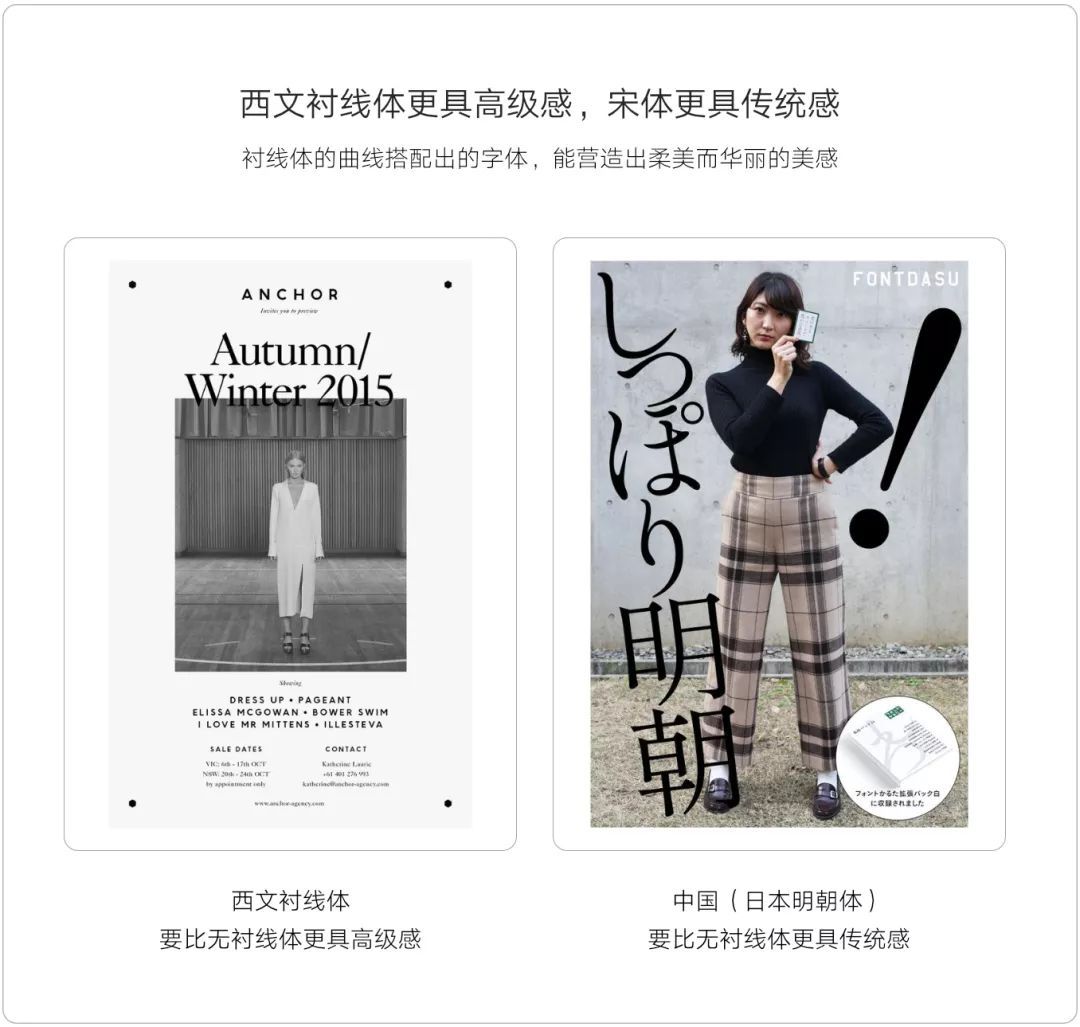
另外想要营造出“高级感”,应要在文字周围多留一些白;在颜色的处理上也不能过于艳丽,降低明度与纯度营造一种沉稳的感觉;文字与文字的距离也不能过窄,尽量让文字之间的距离留多一些白;字号也不能过大,字的颜色要选用灰阶色(黑白灰),颜色也不能过于艳丽。
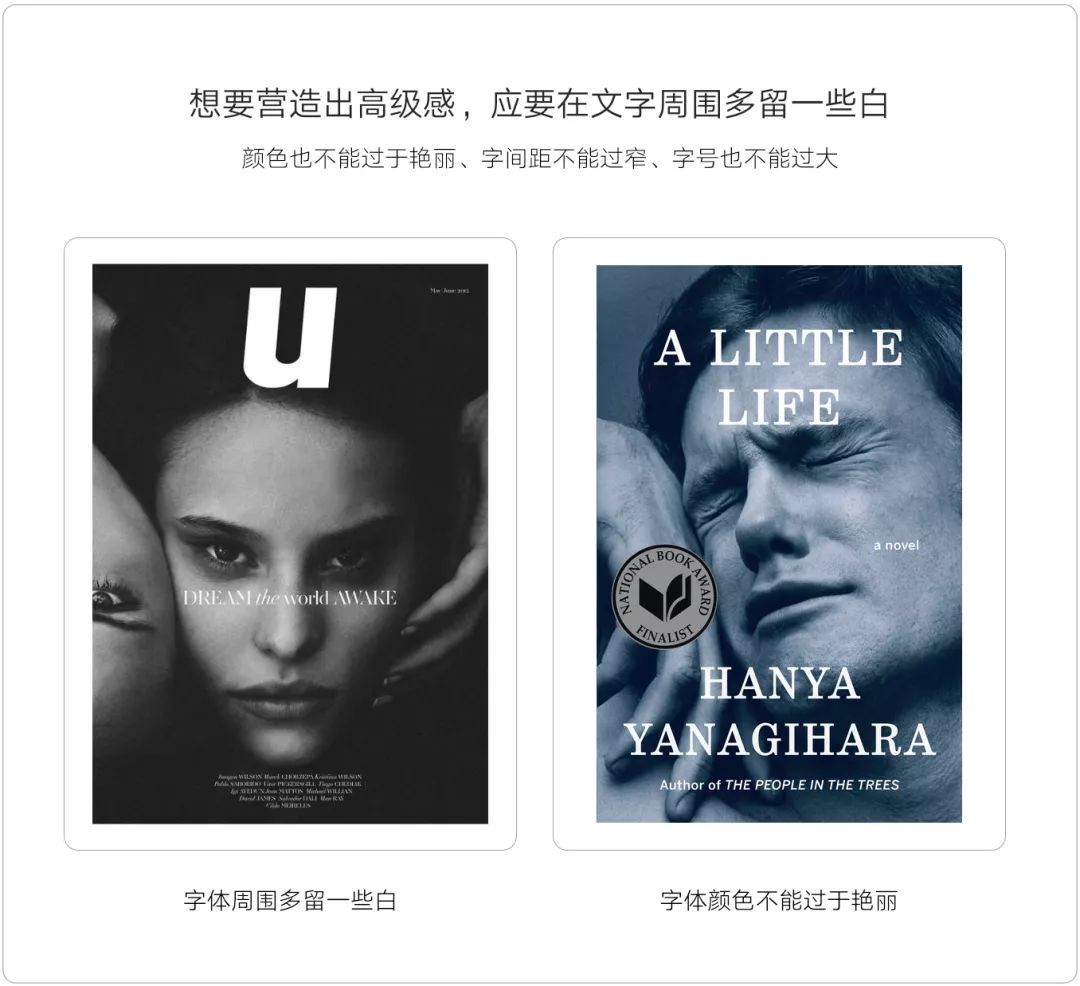
营造高级感也是有一些规则约束的。“配图没有高级感”、“字体选用不对”和“文案与图底关系不明确”都不会营造出高级感。
02《亲密感和柔和感》
生活中如小刀,锥子和针等尖锐的物体会给人一种紧张感和危险感。文字也会让人产生同样的心理。
字体线条越纤细,前端越尖锐,给人感觉就越冰冷,危险,难以靠近的感觉。相反的,不管是在自然界还是在生活中所接触到的人工制品,圆润的形状会给人安全,安心,亲密的感觉。线条粗大,前端越圆润的字体,不会让人感觉到紧张感和危险感。这种字体会给人一种易于亲近,柔和,轻松的感觉。
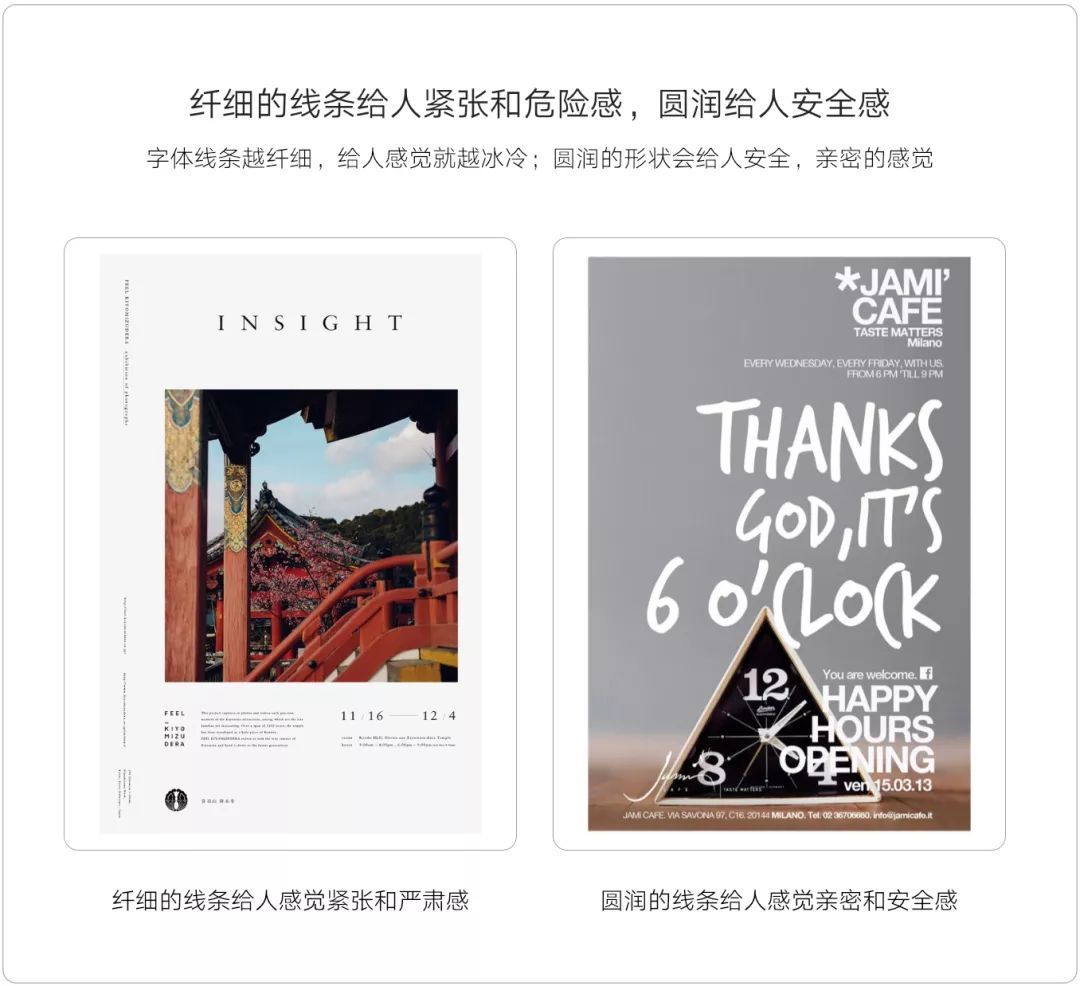
进一步说,如果想加深亲密感和柔和感的印象,可以采用类似手写字的文字设计或样式。我们知道无衬线体(黑体字)要比衬线体(古典字)更具有冷峻感和机械感。
所以用无衬线体不太好营造柔和感,做母婴类等主调较为柔和的项目时尽量用手写体和衬线体,来突出与消费者之间的亲密感和人文感。如果非要用到无衬线体(黑体字),也要尽量采用幼圆的黑体字来营造柔和感。
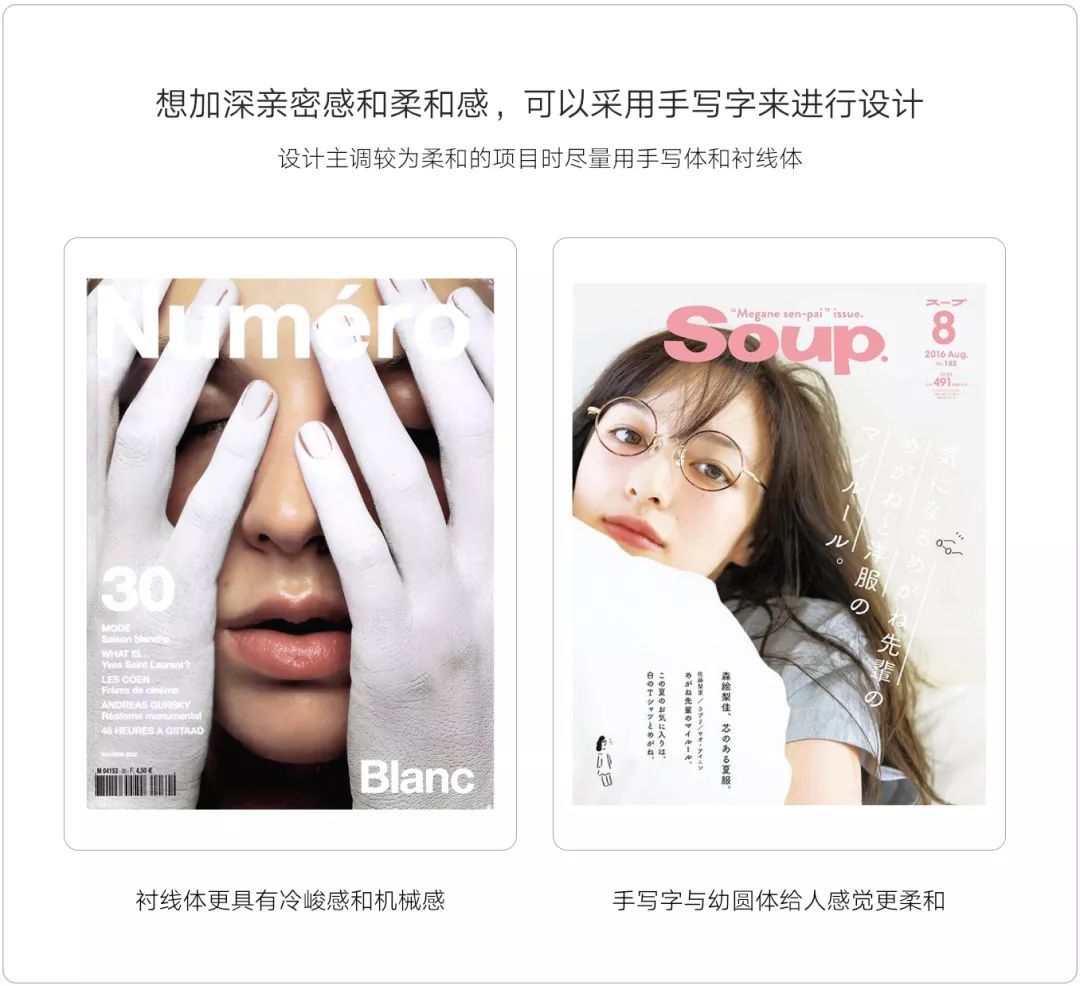
03《未来感和科技感》
文字的构成要素越简单,未来感和科技感的感觉就越强烈。表现科技感时,西文的无衬线体要比衬线体更合适,中文的黑体字要比宋体更合适。但要注意的是,别把正文中的文字不断变得单纯化,这样就不易阅读。
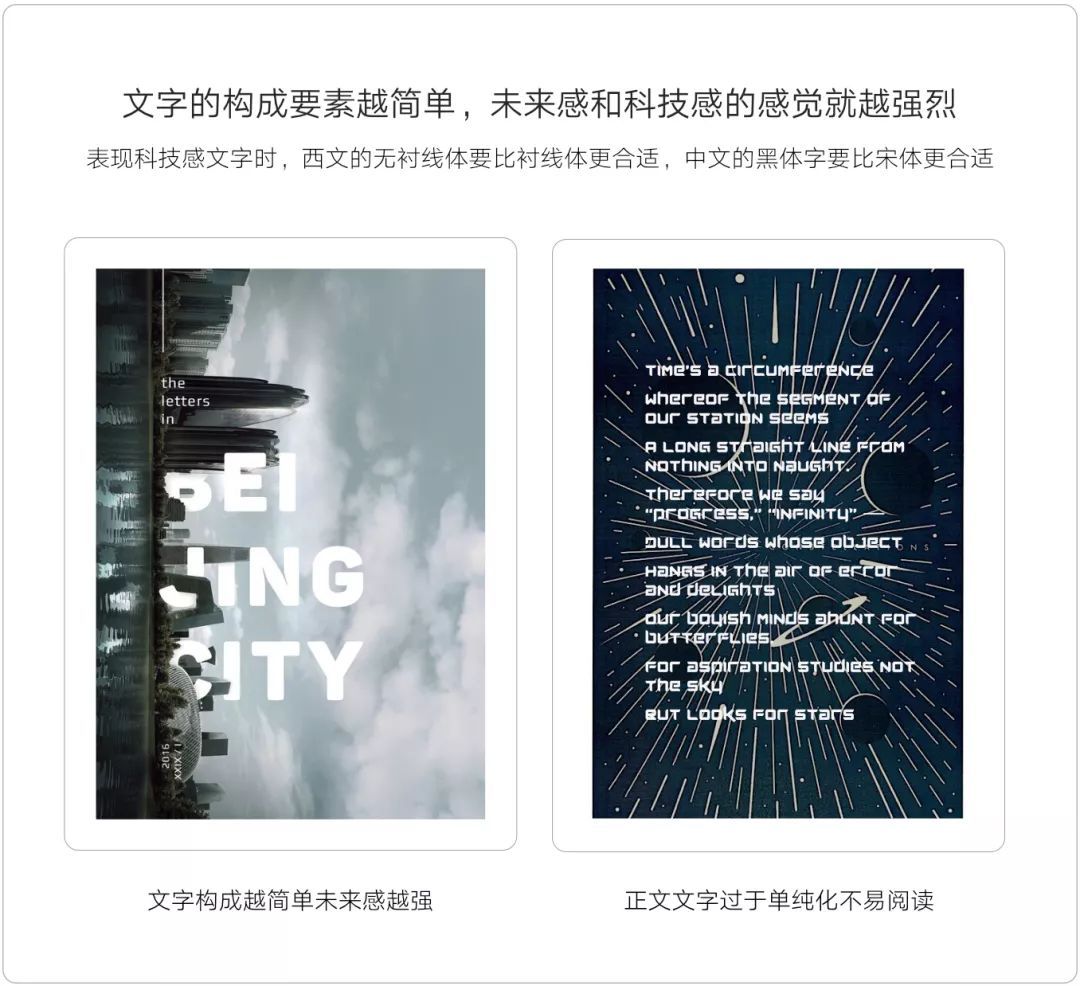
让文字的构成显得更加的简单,或者直接把文字给图形化,更能增强具有未来感的感觉。另外配色的颜色使用过多,科技的印象就会变得非常的弱,因此不要用饱和度和明度过高的颜色,最少采取灰阶色/消色这类无颜色的配色,整体感觉就更加的和谐。
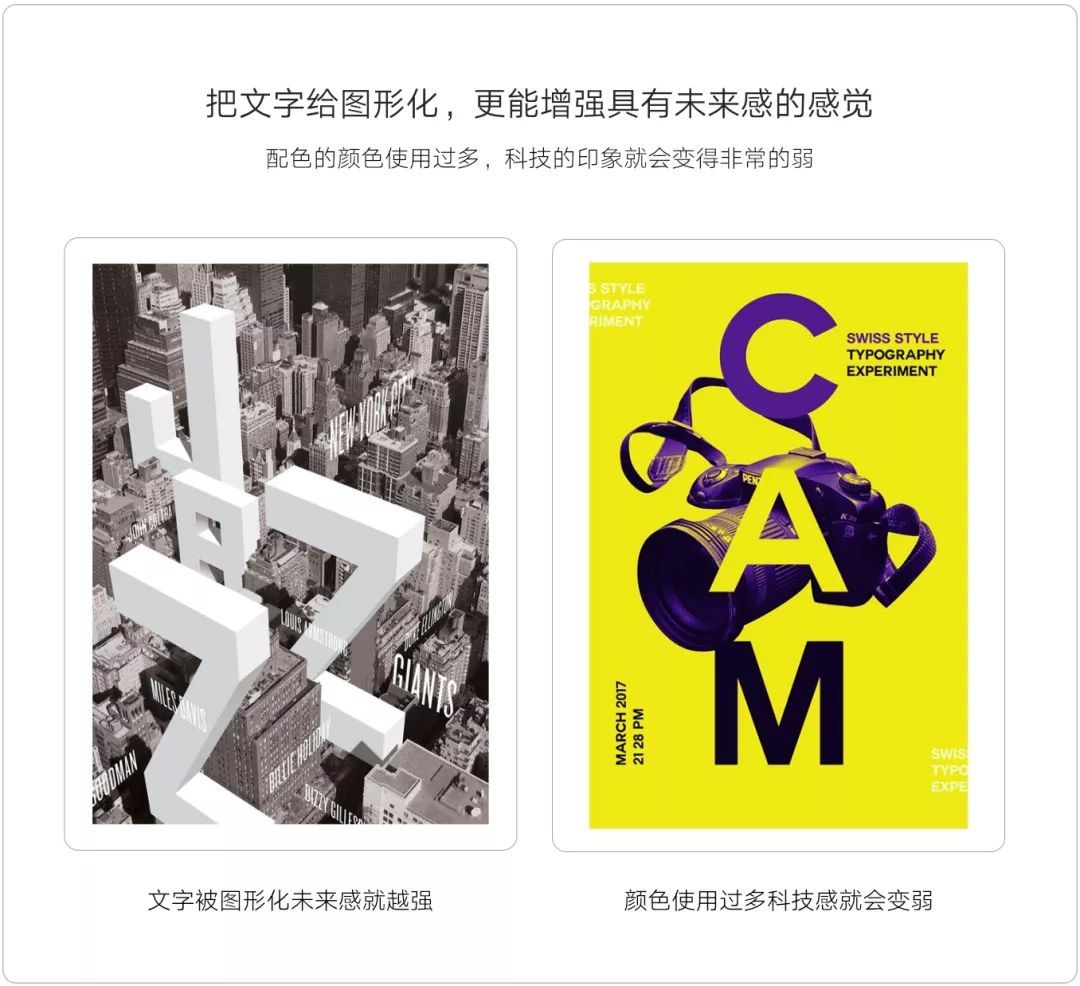
04《情怀感和复古感》
插画与图片的质感随着流行趋势的变化而变化,文字也要符合时代需求的设计。我们选用字体时需要先清楚那个时代的文化特色,巧妙的掌握流行的走向、转变设计的特色,就可以设计出符合特定时代的平面视觉设计效果。
一般来说具有“情怀感”的文字均有种手写字的温暖和柔和感。要注意每种手写字的风格带给人的印象也不同。尖锐的手写字会给人一种理性,思考,判断等感受;而毛笔字会给人一种洒脱,随性,创造,感性等感受。
想要文字表现出复古感,就要从文字的历史角度去考虑,表现复古感就应该采用具有一定历史的字体。从字体角度来讲,采用现代字体(无衬线体或黑体)不能表现出复古感。因此要表现出复古感用具有文化气息的衬线体和历史悠久的字体更为合理。
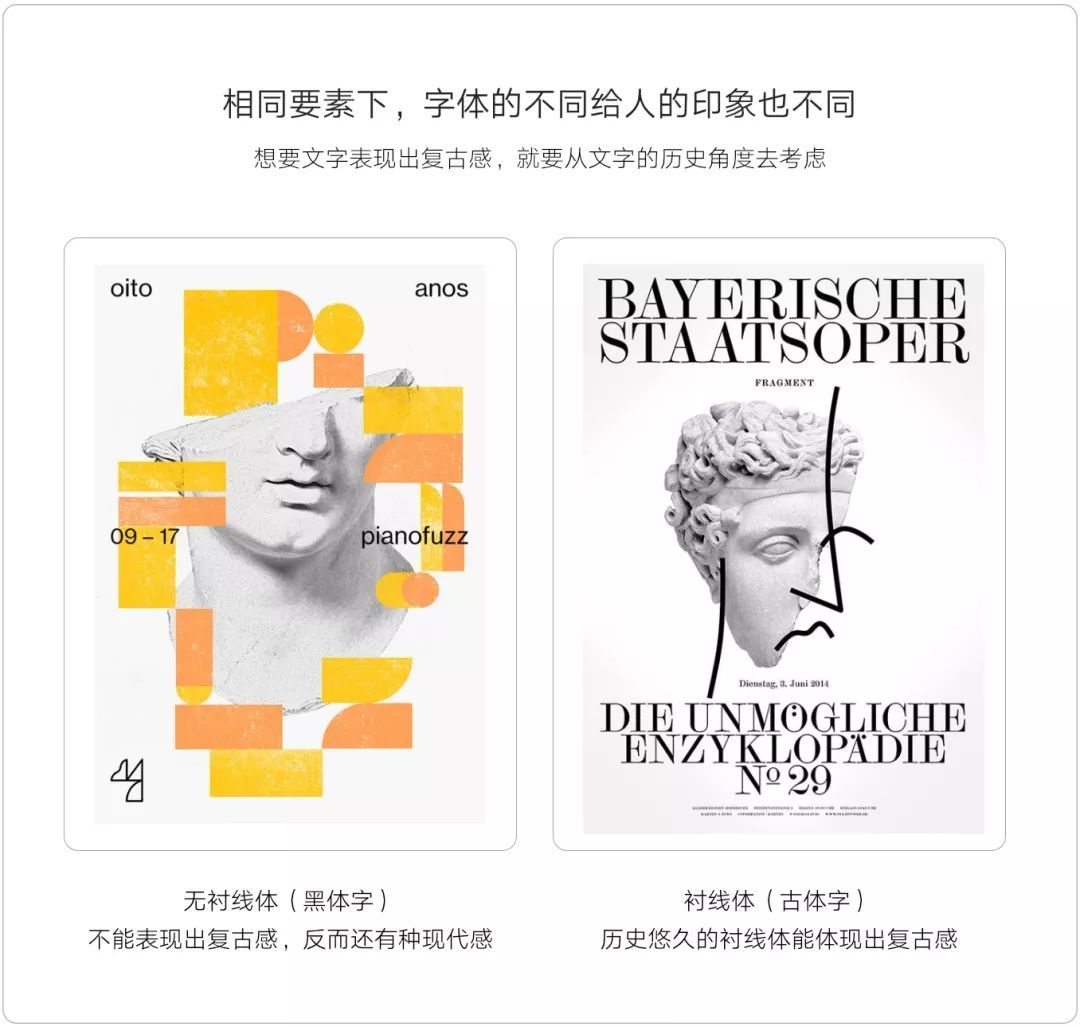
05《装饰性与华丽性》
原本文字就是供人阅读的,但从18世纪后半叶(1750~1800)开始,商家为了吸引客户眼球就不断的强化设计的装饰性,希望文字装饰的差异与其他店家不同,这样才能突显品牌的差异化。从那时候随着文字功能性的提升,设计性也不断被重视。为了吸引用户注意,剧场或店家的广告牌总是以粗大的文字来表现内容。
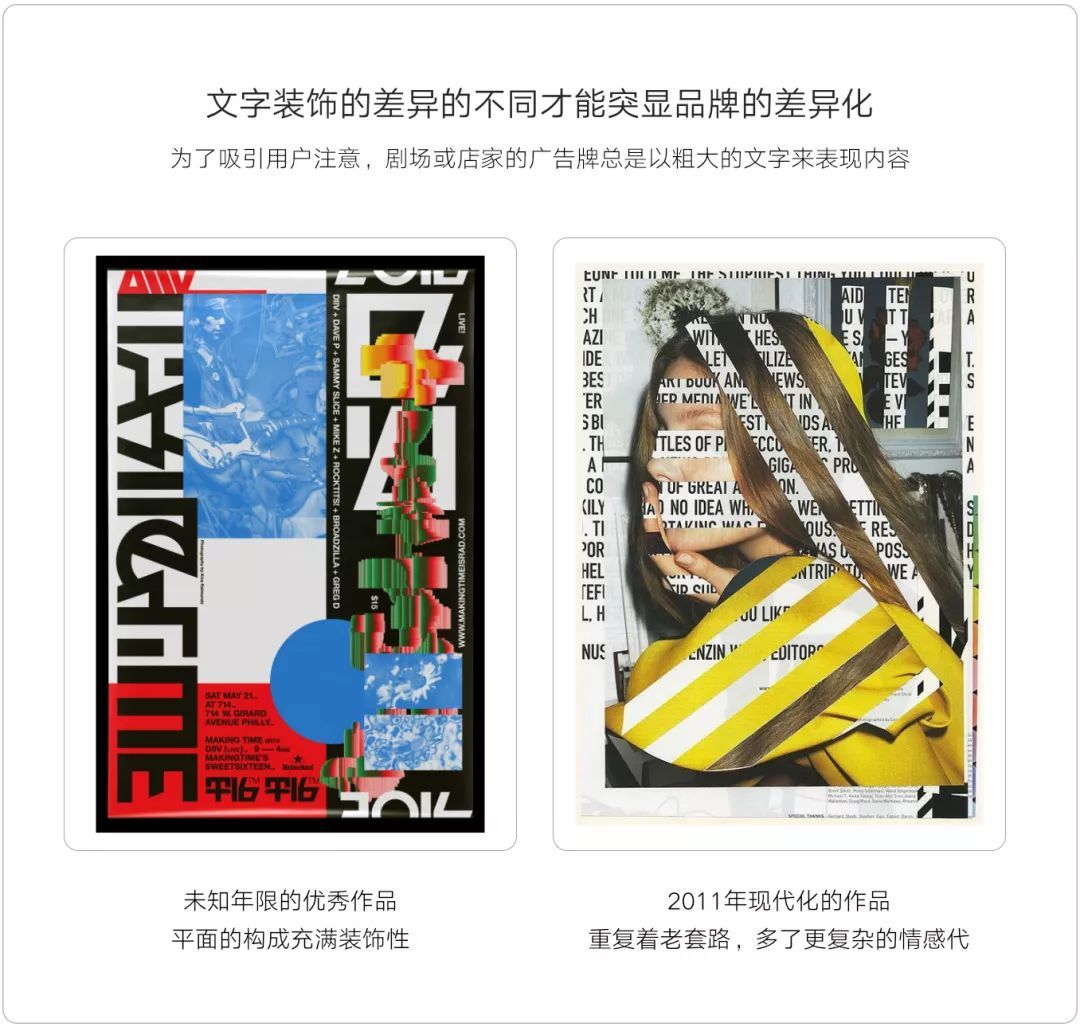
而表现华丽感就要体现在装饰性上。从植物的蔓藤,叶子,羽毛和其他自然景物中取得的灵感,把它们融入到设计中,就可以营造出优美而华丽的感觉。
但要注意的是,装饰性过强的字体不管是用在标题上,还是正文上,都会显得不易阅读并较低读者的可读性,尤其是在正文字体的选择上,尽量不要用装饰性过强的字体。
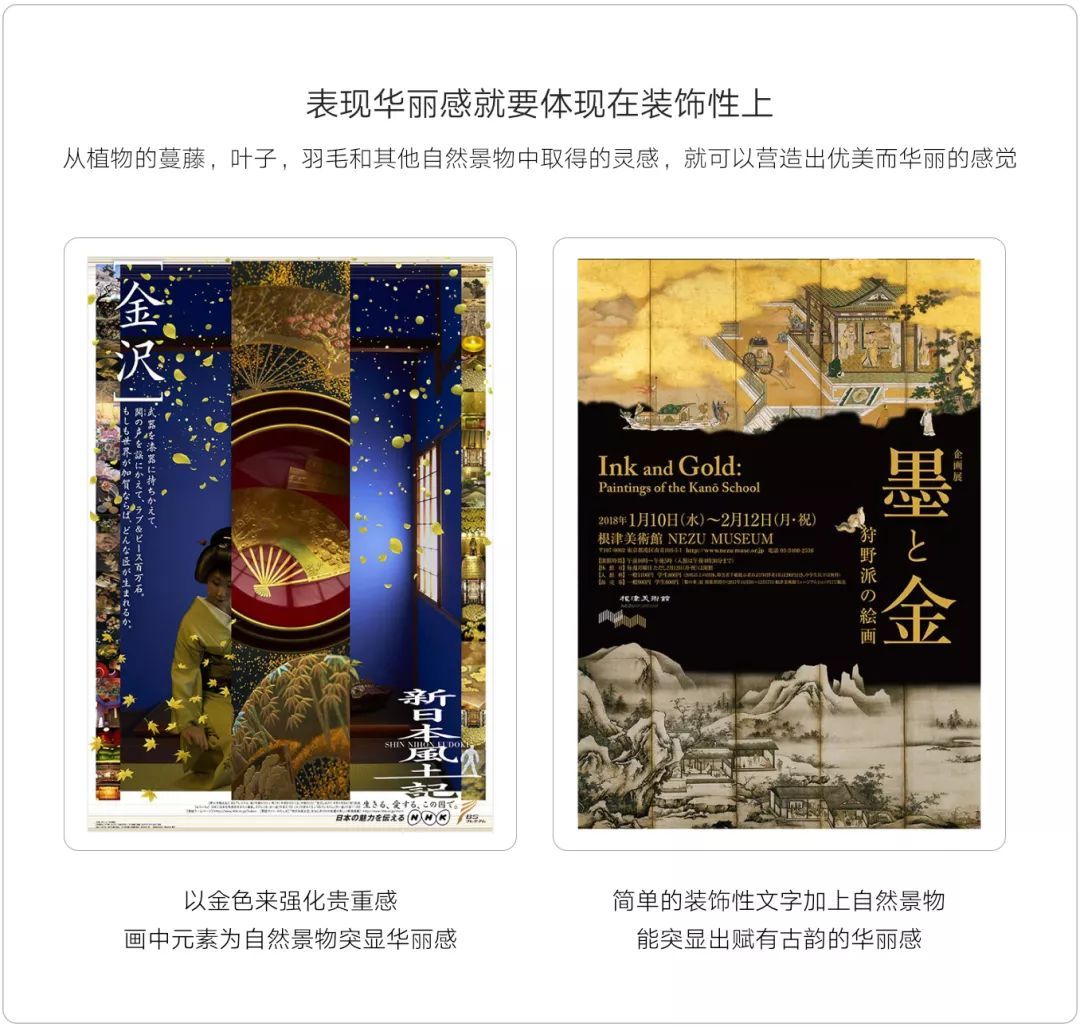
06《传统文化》
传统文化指的是历史文化的沉淀,我国历史悠久文化源远流传,具有代表性的文化传承是书法五体,即楷、行、草、隶、篆,而楷书又分为欧、颜、柳、赵四种字体,并能让人感受到很强烈的文人气息。
期待以后越来越多的设计能传承和弘扬中国艺术与文化,把传统艺术结合现代艺术与科技来表现出来。
除了中国传统的毛笔字外,日本也有被称为江户文字的毛笔字字体,如歌舞伎等剧场广告牌上缩写的勘亭流及单口相声的客寄文字,以及相扑文字,都是为了特定目的而设计的。
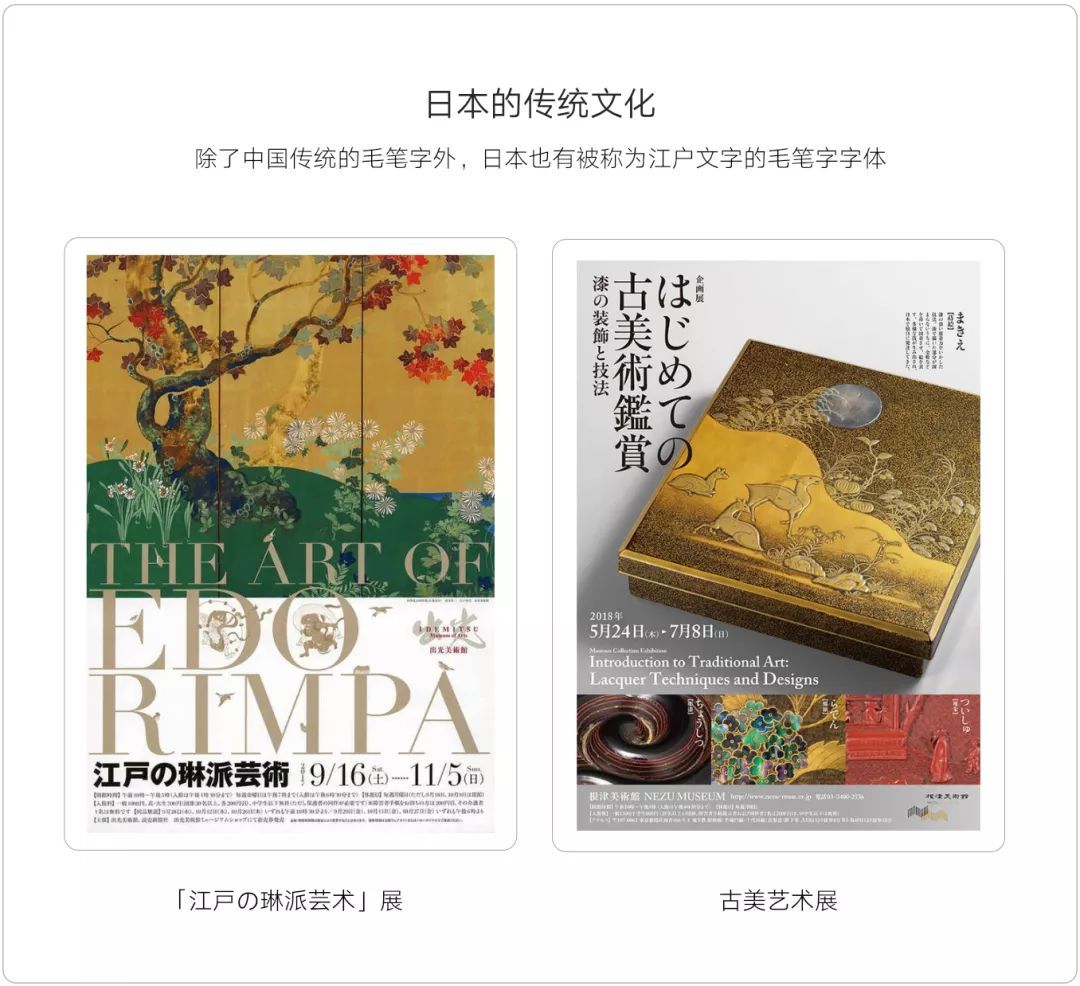
07《严谨感和信赖感》
较为活泼轻松并充满现代感的文字,在吸引目光方面效果显著,但很难让人感到有一定的信赖感。要想塑造出严谨感和信赖感,中文中最好采用宋体这种有历史沉淀的字体,给人感觉很沉稳可靠,同理西文采用衬线体。
在排版时要注意,要将版面设置得更宽松、文字更易读一些。像字间距过近、文字在版面上显得过大,都会给人留下杂乱的印象。另外也要注意,想要营造严谨感和信赖感,配色不可过于跳跃,可选用蓝色、白色、灰色、深色等较为不抢眼的颜色,给人一种轻松的阅读体验。
08《精致的印象》
在文字设计方面,比起宋体和衬线体这类历史悠久的字体,黑体和无衬线体更能给人现代感,利落,清爽的印象。另外,比起粗线条的文字,线条较细的文字能给人留下强烈的纤细感,也相对更细腻精致一些。
下图左面那张图,正因为字体线条较粗设计师在字体上做了斜体处理,就不会显得那么男性化和沉稳的力量感。不做斜体处理就太过男性化了,这么处理能表现出“活泼”与“动势”的感觉,没有那么死板和呆板。而模特穿着中性的感觉也与整体调性呼应,配色标题以黄色、背景以红色为主,诱目色突出动感,整体画面较为和谐。
不论使用哪种文字设计,如果页面布局过于拥挤,整体的设计看上去就会显得更沉闷土气。想解决这个问题就要调整好字号,极力缩减字数,布置的要素尽量力求精简,尽可能留出更多的白,这样便能营造出精致的感觉。配色过多也会显得过于繁杂,要想更好的营造精致感,最好要用灰色来进行处理。